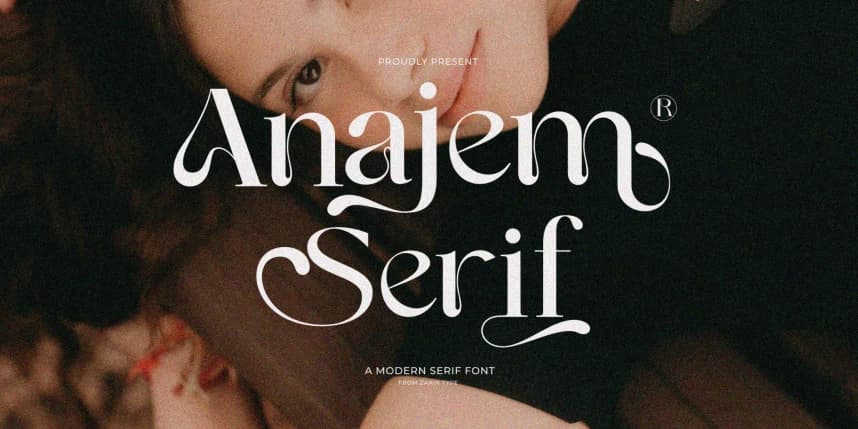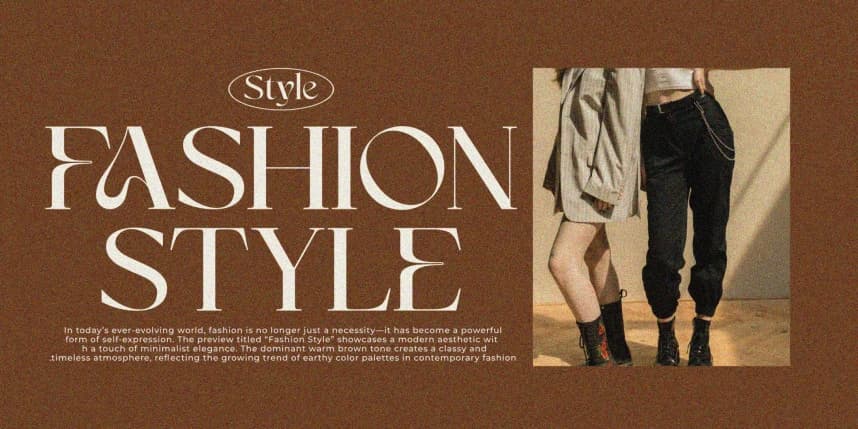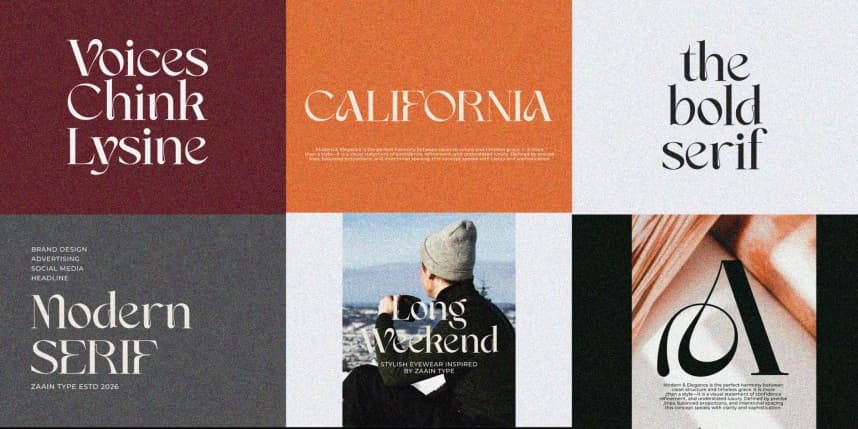
Anajem Serif Font
Anajem Serif Font, klasik zarafeti ince bir modern dokunuşla birleştiren bir serif yazı tipidir. Dengeli oranlar, ince ve kalın çizgiler arasındaki yumuşak kontrast ve zarif fakat ayırt edici seriflerle tasarlanan bu yazı tipi, profesyonel ve sıcak bir hava sunar.
Anajem Serif Font, klasik zarafeti ince bir modern dokunuşla harmanlayan bir serif yazı tipidir. Dengeli oranlara, ince çizgi kontrastına ve zarif fakat ayırt edici seriflere sahip olarak tasarlanan bu font, profesyonel ve sıcak bir his sunar.